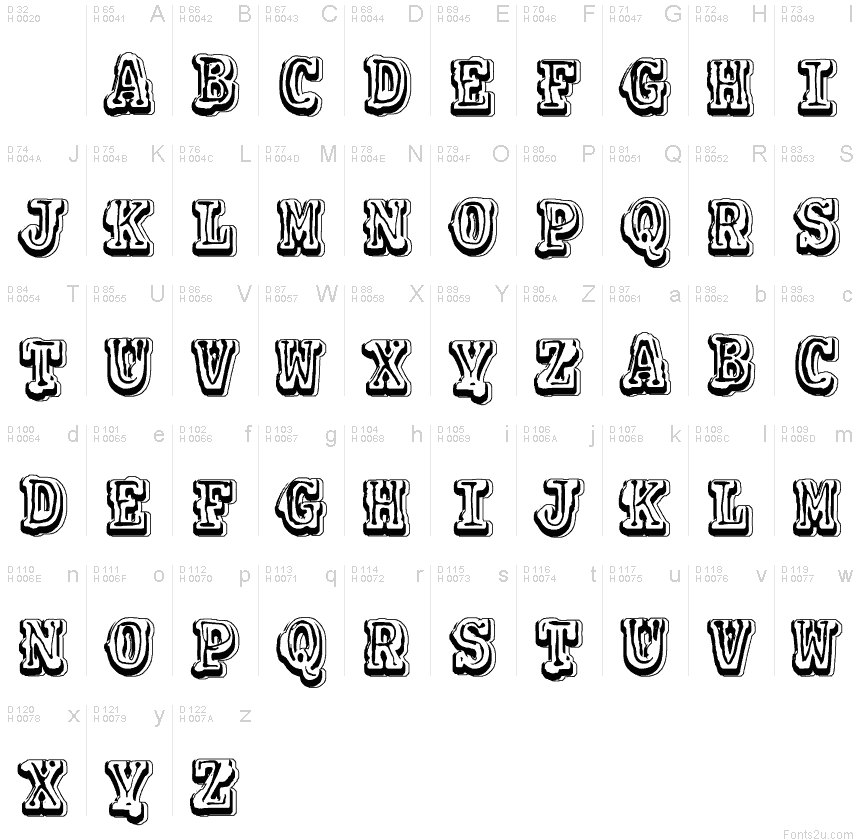
VTKS Colagem autorstwa Douglasa Vitkauskasa to darmowy, surowy krój wyświetlaczowy w stylu western, z grubymi, obrysowanymi literami i efektem ręcznego wycinania, typowym dla starych plakatów. Znaki wyglądają jak wyjęte z dawnych drewnianych szyldów – z nierównymi krawędziami, zaokrąglonymi rogami i grubym, przesuniętym cieniem, który nadaje całości wygląd wycinanki czy kolażu, zamiast typowej, wygładzonej stylizacji retro.
Ten darmowy font świetnie sprawdzi się w projektach, które potrzebują wyrazistego, „zjeżdżonego” charakteru: na plakatach muzycznych, okładkach zina, ulotkach, opakowaniach czy tytułach. Wykorzystaj go tam, gdzie krótkie słowa mają robić robotę – zwłaszcza w nagłówkach czy inicjałach – ponieważ warstwowy obrys i cień nadają nawet kilku literom masywnego, stemplowanego wyrazu.